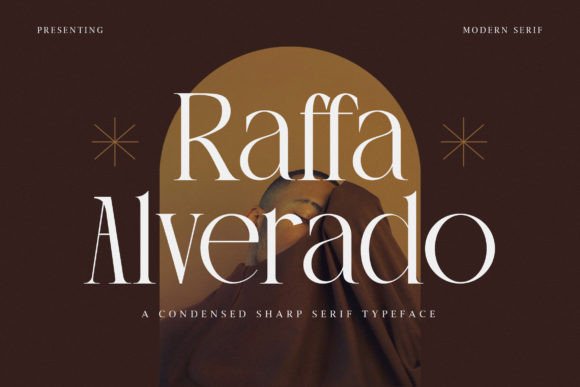
Raffa Alverado
適切なデザイン要素を見つけるのは難しい場合がありますが、Raffa Alveradoは作品を即座に引き立てる優れたコレクションを提供します。
POD(オンデマンド印刷)製品、結婚式の招待状、またはソーシャルメディアのグラフィックを作成している場合でも、Raffa Alveradoは理想的です。